Esistono caratteri simili all’Helvetica? 24 font da non perdere!
Stai progettando le tue etichette o scatole e hai bisogno di un font sans serif pulito e di facile lettura ma sei stufo di usare il buon vecchio font Helvetica? Questo blog è quello che fa al caso tuo. Ci sono infatti alcune informazioni cruciali come i dati relativi al produttore, l’annata, il grado, le informazioni nutrizionali e gli allergeni che hanno bisogno di essere scritti con un font semplice, chiaro e senza troppi fronzoli. Il font Helvetica, nato in Svizzera nel lontano 1957, ha tutte queste caratteristiche, lo sappiamo. Non a caso il font Helvetica è stato utilizzato in innumerevoli situazioni, dall’ambito pubblicitario ed editoriale alla segnaletica urbana. È un font talmente usato da causare a volte la nausea nei progettisti di tutto il mondo. Per questa ragione sono nati nel tempo font sans serif simili che possono essere una valida alternativa. L’obiettivo di questo articolo è proprio quello di mostrarti i font sans serif adatti alla stampa più simili all’Helvetica. Iniziamo.
Arial
Il carattere Arial è considerato forse il sosia per eccellenza del font Helvetica. La grande differenza è sicuramente nell’estremità del font che è angolata e nella spaziatura leggermente maggiore tra i caratteri.
Akzidenz Grotesk
La storia vuole che il font Helvetica sia stato creato come sostituto e concorrente dell’Akzidenz Grotesk. Infatti è indubbio che i due font siano molto simili.
Univers
Il font Univers, progettato da Andrian Frutiger, ha proporzioni e i pesi molto diversi dal font Helvetica. Univers ha anche più spazio tra le lettere rispetto al font Helvetica.
VISIA Pro
Il VISIA Pro è un font geometrico e molto rotondo ma anche molto mininal. La sua leggibilità e chiarezza lo rendono un’alternativa perfetta al font Helvetica.
Noirden Sans
Il Noirden Sans è molto simile al font Helvetica ma leggermente più tondo e più contemporaneo. A primo sguardo è difficile distinguerlo dal font Helvetica.
Exensa Grotesk
Il font Exensa Grotesk è stato definito dai suoi designer Fontastisca il "sans serif autentico". E' un font molto leggibile ed è perfetto sia per i titoli che per testi più lunghi.
Noveltica Nova Pro
Il font Noveltica Nova Pro è un font geometrico che nasce dalla miscela del font Helvetica e del Verdana. E' un font neutro perfetto per numerosi utilizzi.
Lorin
Il font Lorin, ideato da Fontastica, ha un aspetto molto moderno e contemporaneo. E' ideale per quei progetti che vogliono avere un po' di personalità in più.
AS Grammatika
Il font AS Grammatika ha un aspetto vintage-industriale. Esso è un mix perfetto tra il font Helvetiva e il font D-Din. Ha un'aspetto meno rotondo rispetto ad altri presenti in questa lista. Ottimo per le indicazioni ad esempio degli ingredienti.
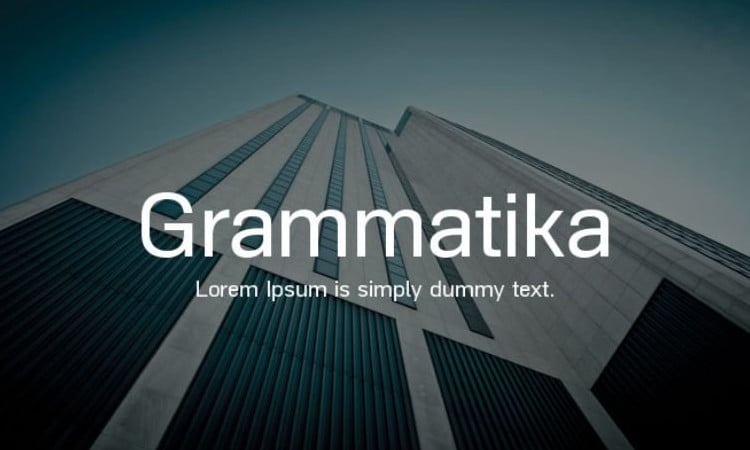
Neue Fofi
Progettato da Arrtde, il font Neue Fofi è un font moderno e geometrico. Ottima alternativa al font Helvetica ma con un aspetto più contemporaneo.
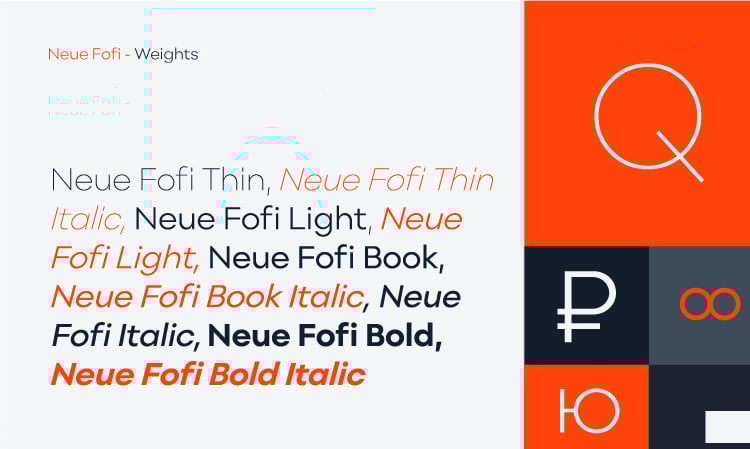
Herz
Il font Herz è leggermente condensato. Esso possiede un aspetto neutro che lo rende perfetto per numerosi utilizzi.
CA Saygon Text
Il font CA Saygon Text è stato progettato con l'obiettivo di garantire facilità di lettura. Esso viene proposto in 5 diversi pesi e stili.
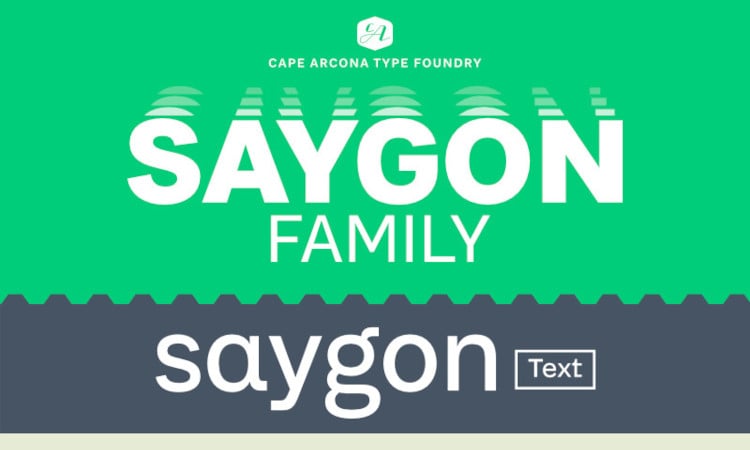
Hamlin
Il font Hamlin è molto minimal e ispirato ai classici font geometrici. Ha un aspetto pulito e stiloso, il che lo rende il font perfetto per un brand o logo.
Grotte
Il font Grotte è disponibile in 3 pesi. Esso presenta glifi utili per diverse lingue tra cui lo Spagnolo, Portoghese, Tedesco, Danese, Francese e Cirillico. Se stai cercando un'alternativa al font Helvetica che supporta più lingue questo è il font che fa per te.
SOLO
Ideato da Unique Foundry, il font SOLO è un font fresco e facile da leggere.
Config
Il font Config possiede una grande famiglia di caratteri. Per l'esattezza si parla di 40 fonts e 10 pesi. Esso possiede un look quasi robotico, per questa ragione è più indicato per l'uso in app e siti web.
Oxford
Il font Oxford disegnato dal designer jenwagnerco, è un font essenziale e di qualità. Nonostante si discosti molto dagli altri, esso mantiene il minimalismo e la leggibilità tipica del font Helvetica.
ARS Maquette
Il carattere ARS Maquette è un font di tipo grotesque progettato da Angus R. Esso ricorda molto i font Proxima Nova e Gotham.
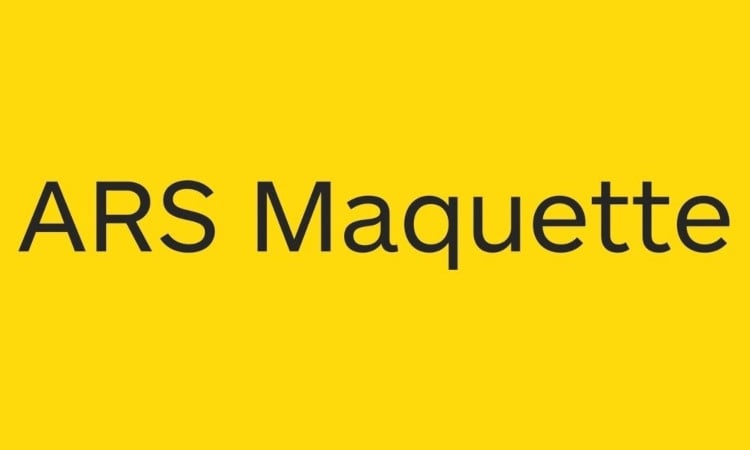
Brandon Grotesque
Il carattere Brandon Grotesque è stato progettato dal designer tedesco Hannes von Döhren e pubblicato nel 2010. E' un font molto utilizzato e interessante.
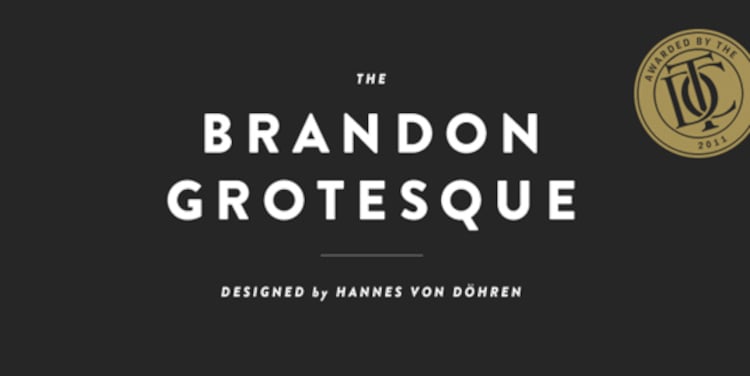
FF Bau
Progettato da Christian Schwartz nel 2002, il font FF Bau è una grande famiglia di caratteri sans serif disegnati nel genere "Grotesk".
National
Il font National è un sans serif ingannevolmente semplice con dettagli sottili che gli conferiscono una personalità distintiva, ma non distraente. E' un font adatto alla lettura di testi lunghi di piccoli dimensioni.
Proxima Nova
Proxima Nova (2005) colma il divario tra caratteri tipografici come Futura e Akzidenz Grotesk. Il risultato è un ibrido che combina proporzioni moderne con un aspetto geometrico.
Slate
Il font Slate, progettato dal pluripremiato Rod Mcdonald, è un carattere davvero bello che raggiunge livelli stellari di leggibilità, su stampa e su schermo.
Speriamo che questa guida ti abbia permesso di trovare il font sostitutivo all'Helvetica che stavi aspettando